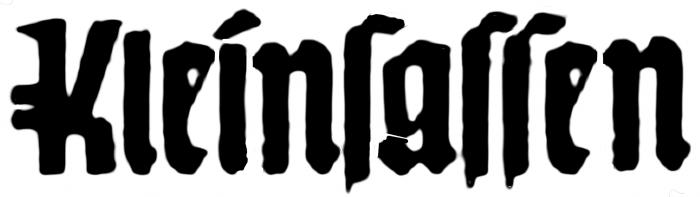
Gebrochene Schrift mit langem s gesucht
und die Bitte um Hilfe bei der Identifikation einer Schriftart.
Ich habe für das Wort "Kleinsassen" folgendes Schriftbild:
leider ist das, nicht mehr vorhandene, Original immer wieder von Kopie zu Kopie verwendet worden.
Die Qualität ist dementsprechend.
Auch kann ich nicht sagen, ob für das Original eine vorhandene Schrift genutzt oder neu gezeichnet wurde.
Eine Abfrage bei WhatTheFont brachte mich auch nicht weiter.
Vielleicht hat einer von Euch eine Idee, denn das K ist ja ziemlich markant.
Und wie wurde das verwendet? War das wirklich ein gedruckter Text oder ein Schild oder …?
Es war ein Aufkleber.
Edit: Wenn jemand auch was zur der umlaufenden Schriftart sagen kann, wäre das auch toll.
Ich sehe da kein a.
Es soll aber eines sein, zwischen den langen s
So wird es dann wohl enden.
Aber unverhofft kommt oft, vielleicht weiß noch einer etwas, ich habe die Frage ja erst heute Vormittag eingestellt.